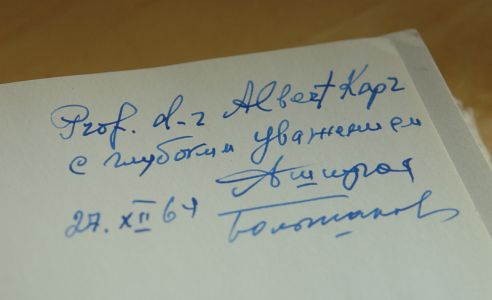
Unwahrscheinlich, aber weiß jemand was darüber?
Argh! Musst du uns das zeigen? Jetzt will ich das auch haben! :roll:
Was man so im Netz liest, klingt ja recht vielversprechend:
I recommend getting Yuri Gordon’s “Book of Letters From Аа to Яя”. The text is in Russian only, but the book is richly illustrated.
I’ve seen it, and I love it. Its concept is somewhat similar to Karen Cheng’s book, but Gordon analyzes each Cyrillic letter one-by-one in different styles, and he also includes samples from various Russian logos and calligraphic creations. This gives you a very fair overview of the extent to which you can experiment with Cyrillic forms while staying within the boundaries of what the Russian reader considers “normal”.
„The Moscow Times“
Das Cyrillesche Alphabet gebe Texten einen eckiges, monumentales Aussehen, verlangsame das Lesen und sei dem Lateinischen Alphabet damit unterlegen, behaupte Yury Gordon in seinem neuen Buch „Book on Letters from Аа to Яя“. Brian Droitcour bespricht den „dicken Wälzer, der geschickt zwischen Theorie und Praxis balanciert“. Gordon, dessen Designfirma „Letterhead“ 200 eigene russische Schriftarten kreiert hat, widme den Großteil seines Buches der Erforschung, was Cyrillesche Buchstaben können und was nicht, fasst der Rezensent zusammen. Es sei eine Auswahl nützlicher Tipps für professionelles Arbeiten mit der Gestalt Cyrillescher Buchstaben, was sich generell als schwierig erweise, da Cyrill und Methodius hervorragende Linguisten aber grauenhafte Designer gewesen seien“, so der Autor. Jedes Kapitel beginne mit einem historischen Panorama zum jeweiligen Buchstaben der verschiedenen russischen Schriftarten. Fülle und Vielfalt bildhafter Beispiele würden das Buch laientauglich gestalten, befindet der Rezensent, vor allem aber warte der Autor mit praktischen Hinweisen für Designer auf.
Allerdings ist es wahrscheinlich sehr schade, wenn man die sicher sehr spannenden Texte nicht versteht. Vielleicht gibts ja irgendwann mal eine Übersetzung.
Ich hab mal ein ganz ähnliches Buch von 1964 über die kyrillische Schrift erstanden:
Ein echter typophiler Leckerbissen!
Vorn ist eine Widmung von/für/über(?) Albert Kapr drin. Kann das jemand lesen?
PDF und Detailbeschreibung hast du ja gesehen nehme ich an?
Dass ich es haben will ist klar :)
Die Frage ist nur, ob es nicht mal eine englische Fassung davon gibt...
Dann würde man sich ärgern hätte man die russische gekauft. Andererseits hätte man so einige wahrscheinlich gut gestaltete Textbeispiele in kyrillisch, was auch kein Schaden wäre.
Wie es aussieht ist das Buch jetzt verfügbar.
Jetzt sollte man es nur noch lesen können :)